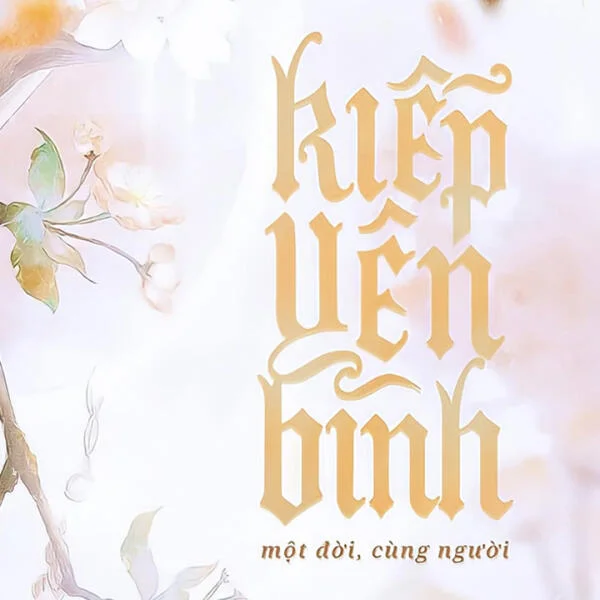
Download Font Cethik Việt Hóa - Font đẹp lắm luôn
Font Cethik là một phông chữ hiển thị cực kỳ thú vị và chân thực. Phông chữ này được làm thủ công gọn gàng và có độ chi tiết cao. Cethik được mã hóa PUA có nghĩa là bạn có thể truy cập tất cả các glyph và swash một cách dễ dàng!
Tổng quan về Font Cethik
Font việt hóa Cethik là một phông chữ display cực kỳ thú vị và chân thực lấy cảm hứng từ font chữ gothic đầu những năm 1900. Phông được thiết kế hoàn toàn thủ công với các nét chữ có độ chi tiết cao và rất độc đáo.
Cethik được mã hóa PUA vì vậy bạn có thể truy cập tất cả các glyph và swash rất dễ dàng. Font Cethik Việt Hóa đầy đủ bởi FZ, phù hợp cho các thiết kế tiêu đề, bìa truyện, typo, tạp chí...
Font Cethik Việt Hóa siêu đẹp
Mẫu 1
Font việt hóa Cethik
Mẫu 2
Mang việt hóa mang phong cách gothic
Mẫu 3
Mẫu 4
Mẫu 5
Chi tiết ký tự của Font Cethik
Font Cethik - Character
Chi tiết ký tự 1
Chi tiết ký tự 2
Font Cethik Alternatives
Chi tiết ký tự 3